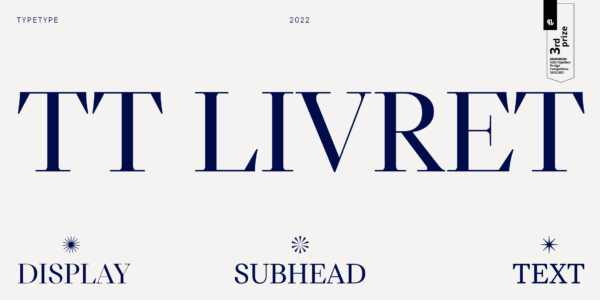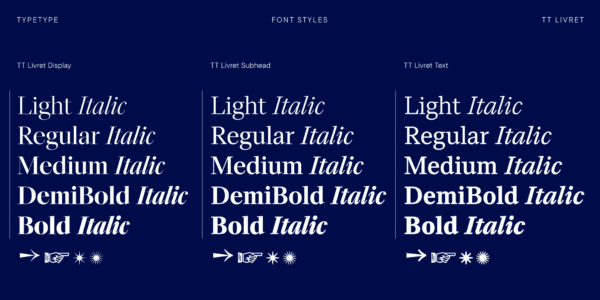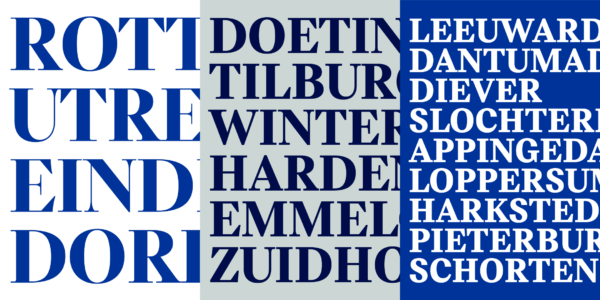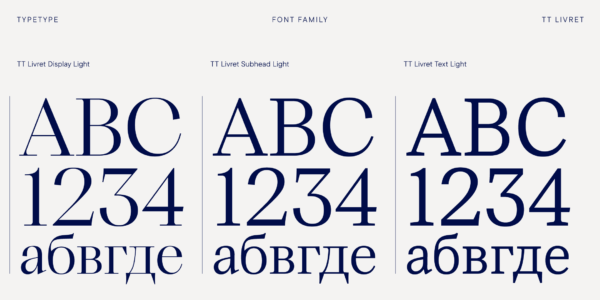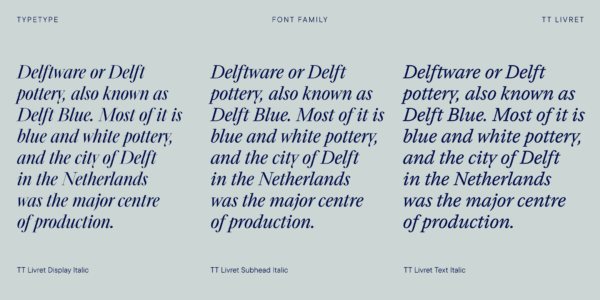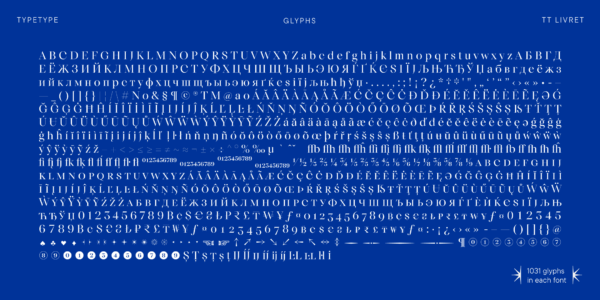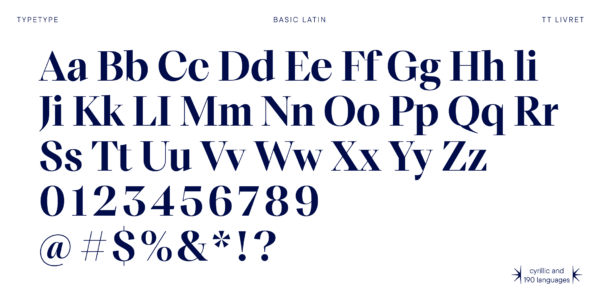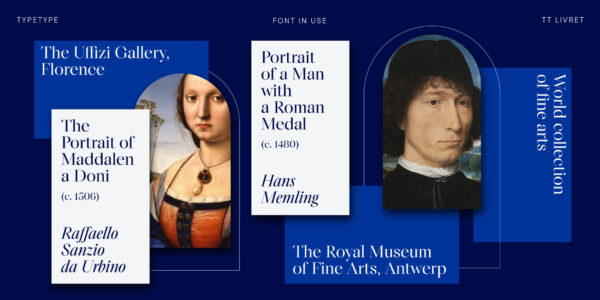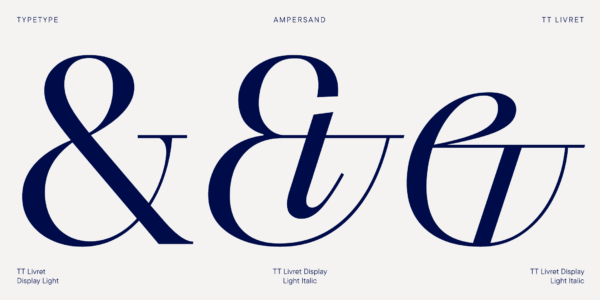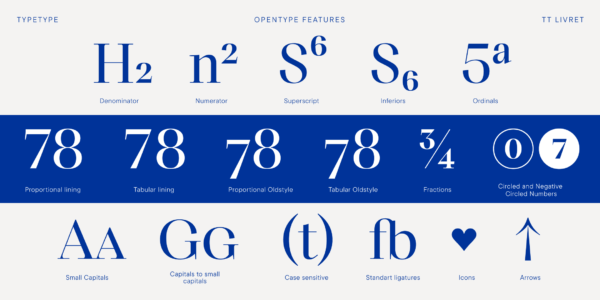
TT Livret
TT Livret — ТТ Ливрет
Произносится «ТТ Ливрет». «Livret» — производное слово от le livret, в переводе с французского «книжечка». Буквы «TT» являются аббревиатурой названия компании.
TT Livret — изящная и универсальная антиква. Гарнитура включает спокойное текстовое и выразительное дисплейное подсемейства.
Текстовое подсемейство обладает равноширинными пропорциями и спокойным характером, овальными круглыми знаками, свободным спейсингом и более открытыми апертурами. В глянцевом дисплейном подсемействе пропорции разноширинные, круглые знаки максимально близки к кругу, апертуры закрытые, а спейсинг плотный. В шрифте присутствует промежуточное подсемейство — Subhead, которое может выглядеть более спокойно как текстовое или быть контрастным и использоваться как дисплейное.
TT Livret — изящная, современная и функциональная антиква со спокойным текстовым и выразительным дисплейным подсемействами.
Шрифтовая гарнитура TT Livret состоит из 32 начертаний
В TT Livret мы воплотили идею антиквы, которой будет комфортно пользоваться в современных реалиях.
Если вы всё ещё думаете, что антиква — это шрифт с выраженным историческим характером, сложный для применения в современных реалиях, встречайте новую гарнитуру от TypeType!
TT Livret — изящная, современная и функциональная антиква со спокойным текстовым и выразительным дисплейным подсемействами.
Эта шрифтовая гарнитура гармонично выглядит в книгах и других периодических изданиях, на постерах или на обложках журналов. Область применения не ограничивается только печатной индустрией, ведь TT Livret эстетично смотрится везде, где используется текст.
Текстовое подсемейство обладает равноширинными пропорциями и спокойным характером, овальными круглыми знаками, свободным спейсингом и более открытыми апертурами. В глянцевом дисплейном подсемействе пропорции разноширинные, круглые знаки максимально близки к кругу, апертуры закрытые, а спейсинг плотный. В шрифте присутствует промежуточное подсемейство — Subhead, которое может выглядеть более спокойно как текстовое или быть контрастным и использоваться как дисплейное.
В TT Livret мы воплотили идею антиквы, которой будет комфортно пользоваться в современных реалиях. Это функциональный шрифт, где текстовое начертание не отвлекает от чтения, а дисплейное, наоборот, притягивает внимание.
Шрифтовая гарнитура TT Livret состоит из 32 начертаний: 15 прямых начертаний, 15 наклонных начертаний и 2 вариативных шрифта. В каждом начертании — 1031 глифов. Шрифт содержит 26 OpenType фич, а также большое количество лигатур. В курсивных начертаниях много альтернативных знаков, которые особенно разнообразно представлены в кириллице.